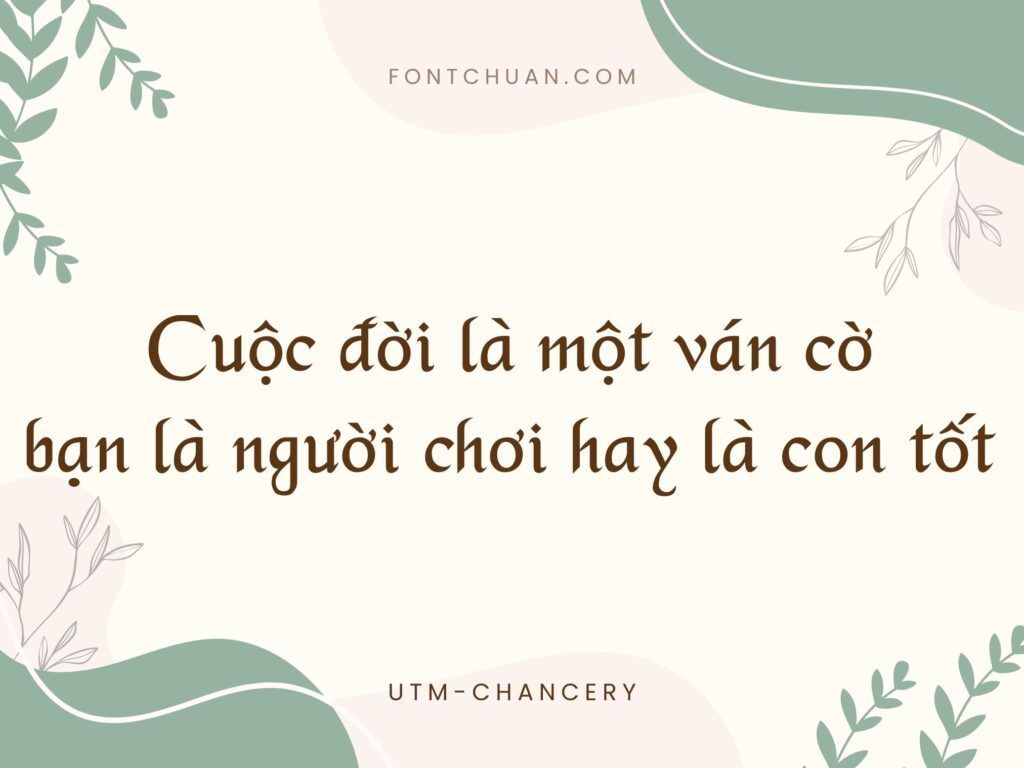
Font UTM Chancery Việt Hóa
Việt hóa bởi: Đinh Kiên
UTM Chancery là một Font Script mang phong cách Font Handwritten cổ điển, phiên bản Việt hóa của font chữ Chancery – kiểu chữ lấy cảm hứng từ thư pháp Ý thời kỳ Phục Hưng. Font này nổi bật với các ký tự nghiêng, đường nét mềm mại và uyển chuyển, tạo cảm giác trang nhã và lịch sự. Phiên bản Việt hóa đã được thực hiện bởi Đinh Kiên, hỗ trợ đầy đủ tiếng Việt cùng hơn 100 ngôn ngữ khác. Đây là một trong những font được cộng đồng thiết kế sưu tầm và chọn lọc nhằm đáp ứng nhu cầu đa dạng trong thiết kế.
UTM Chancery có cấu trúc chữ với các nét thanh mảnh và độ nghiêng nhẹ, tạo nên sự hài hòa và dễ đọc. Font này phù hợp cho các ứng dụng như thiết kế thiệp mời, chứng chỉ, bằng khen, tiêu đề và các ấn phẩm in ấn yêu cầu sự trang trọng và nghệ thuật. Các ngành nghề như quảng cáo, giáo dục, công nghệ và bất động sản có thể tận dụng UTM Chancery để tạo điểm nhấn độc đáo trong thiết kế.
Tác giả: Muhammad Sirojuddin